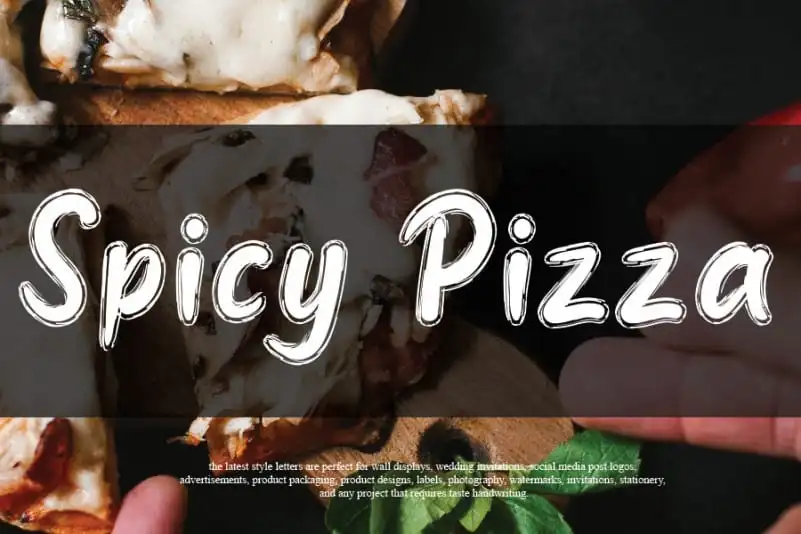
Spicy Pizza Script Font – Download Grátis
A Spicy Pizza Script Font é uma fonte escrita a mão que captura os melhores elementos do estilo serigrafado, mas mantém-se atual e renovadora. Este design elegante e sofisticado se destaca para projetos que desejam um toque autêntico e único. Ideal para adicionar aquela pitada de personalidade em texturas variadas, seja em títulos grandiosos ou linhas menores. Que tal incorporar esta fonte em suas próximas criações? Ela certamente trará seu trabalho a um nível superior.